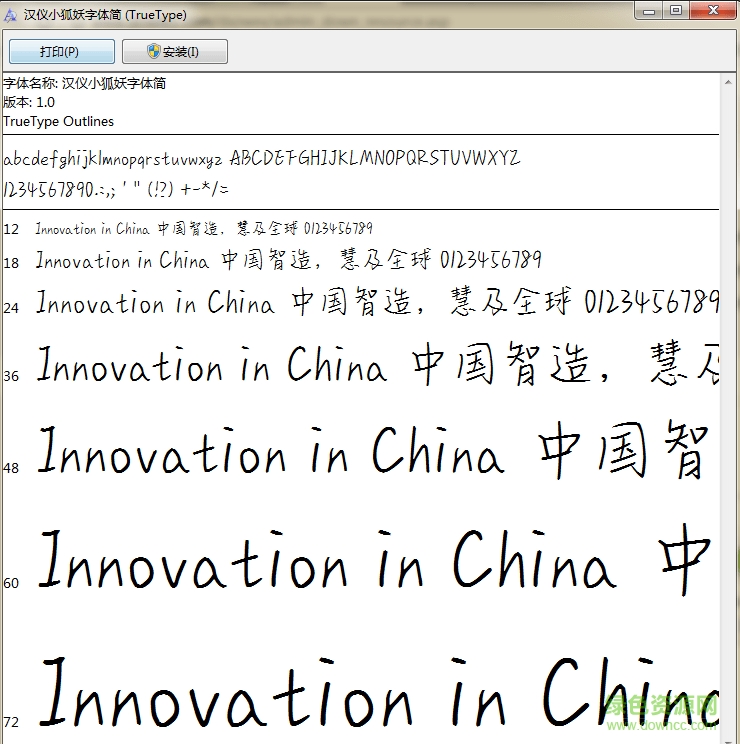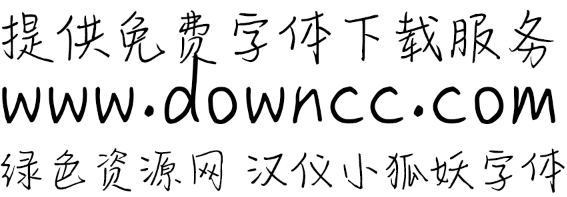
漢儀小狐妖字體
小狐妖字體ttf在各類打印產(chǎn)業(yè)中,媒體設(shè)計(jì)中,各類字幕制作中,或者寫(xiě)作過(guò)程中都廣受用戶的喜愛(ài),運(yùn)用廣泛,能夠達(dá)到很有效的視覺(jué)體驗(yàn),讓你感受到一種隨性的視覺(jué)效果!
漢儀小狐妖體ttf介紹
這款字體擁有簡(jiǎn)約時(shí)尚的效果,使用過(guò)后能夠十分醒目,讓用戶達(dá)到一種更好的視覺(jué)體驗(yàn),擁有數(shù)字英文以及簡(jiǎn)體中文的顯示效果!
漢儀小狐妖體ttf
特色介紹
1、這款字體行云流水將讓你感受到最佳的字體使用體驗(yàn)
2、擁有很優(yōu)秀的視覺(jué)效果
3、讓你在各類場(chǎng)合都能夠應(yīng)用
字體發(fā)展